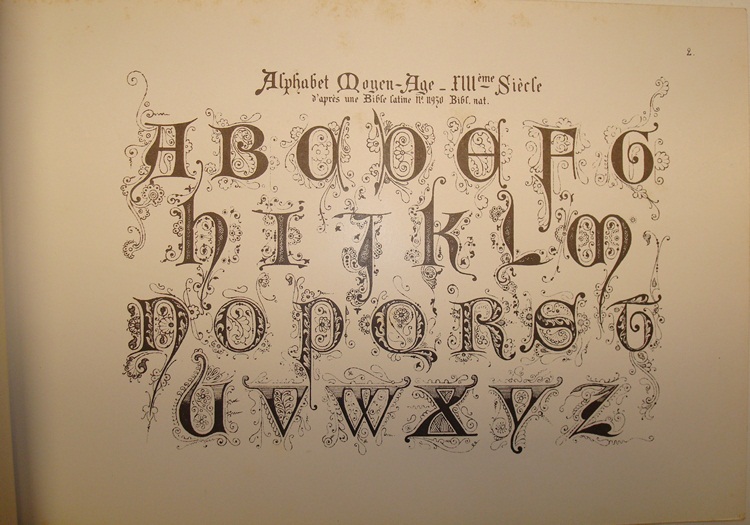
| Detalle de una de la cromolitografías |
En esta segunda parte dedicada a Ernest Guillot reproducimos los dos álbumes que completan la colección descrita en la primera parte de este blog
GUILLOT, E. "ELEMENTS D'ORNAMENTATION DU XVI SIÉGLE-"
Completa la colección descrita en la primera parte de este artículo, dedicada a la edad media y el renacimiento.
GUILLOT, E. "ALPHABETE de Style Moyen-Age -Renaisance"
Paris: Monrocq Frères, finales s. XIX, 1 Vol. (numerado: 6473) Alfabetos de los siglos XI hasta el XVI.
| Inicial Guillot. |